왕은실 캘리그라피.1_손으로 마음을 쓰기 위해 알아야 할 것들
캘리그라피
“캘리그라피가 뭐야?”
포스터, 책 표지, 포장, 광고 등 시각디자인 영역에서 캘리그라피가 많이 활용되고 있지만 위 질문을 자주 받곤 합니다. 쉽게 설명하자면, 캘리그라피는 문방사우(文房四友)와 그 외 다양한 도구들을 이용해 컨셉트를 잡아 손으로 글자를 디자인하는 과정이라고 정의할 수 있습니다. 붓과 먹으로만 작업을 한다고 생각할 수 있지만 그렇지 않습니다. 기본적으로는 먹과 붓을 이용해 글자들을 쓰고 만들지만 잉크, 물감, 나무젓가락, 칫솔, 색연필 등 다양한 도구와 소품을 이용하기도 하죠. 제가 최근에 진행한 광고와 표지, 포스터 작업 사례를 살펴보겠습니다.
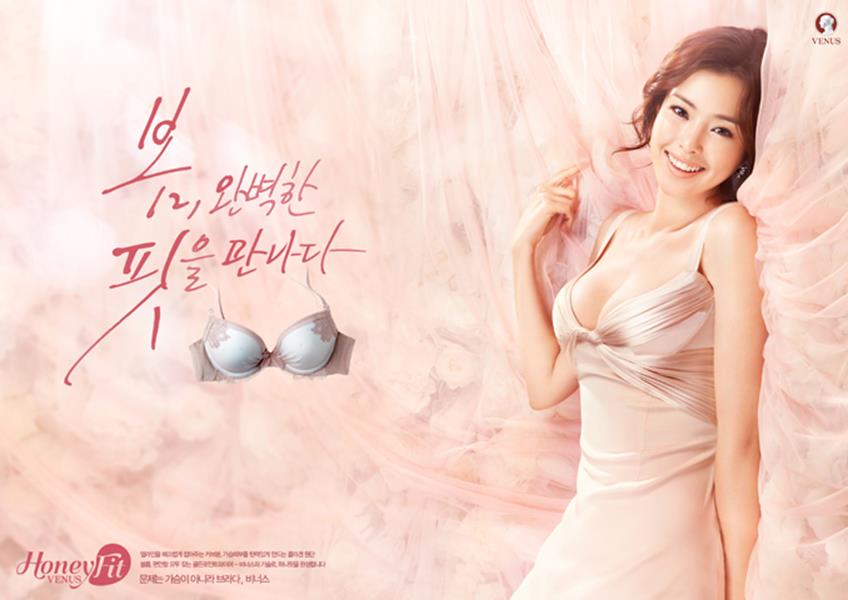
비너스 잡지 광고에 들어간 캘리그라피. 나무젓가락과 A4용지를 이용해 작업했다
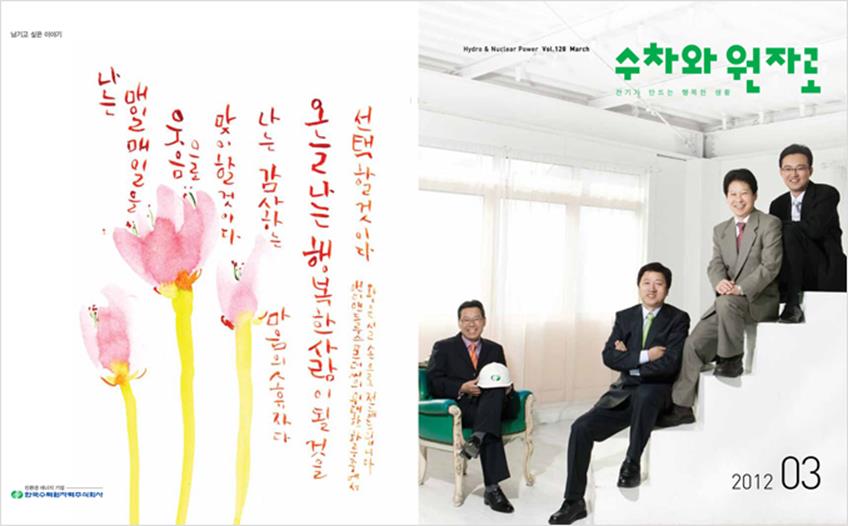
한국수력원자력주식회사 사보 <수차와 원자로> 3월호. 그림은 동양화물감으로 판화지에 그렸고, 글씨는 세필을 사용해 동양화물감으로 썼다
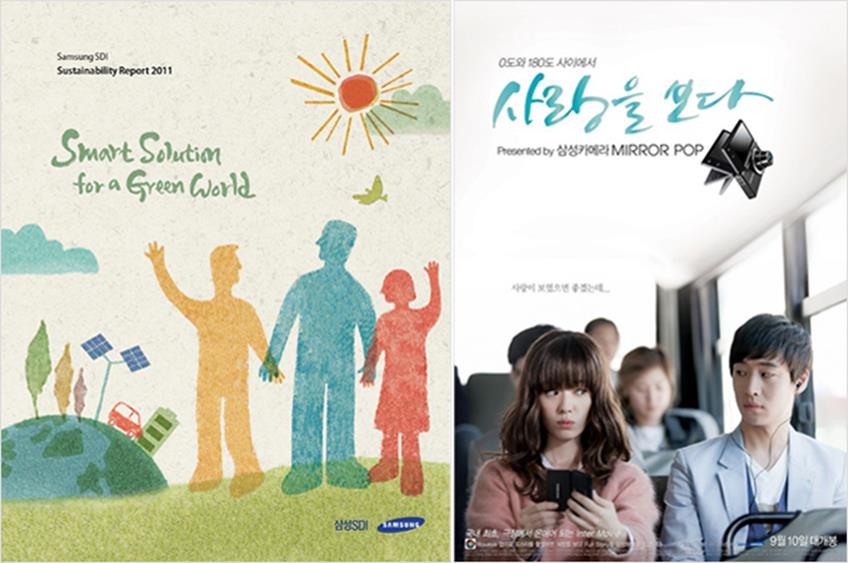
(왼쪽) 삼성카메라 미러팝 광고 작업. 수채화 물감으로 스케치북에 세필을 이용하여 작업했다. (오른쪽) 삼성SDI 사보표지. 갖고 있던 드로잉북에 물감을 사용해 작업한 사례.
최종적으로 선택된 글씨와 그림만 본다면 결과물은 하나입니다. 하지만 시안을 만들 때 여러 시도를 하게 되는데요. 붓은 기본이고, 세필, 붓펜, 나무젓가락 등을 이용해 컨셉트에 맞게 보통 다섯 개 내외의 시안을 만들어 클라이언트에게 선택권을 줍니다.
서예와 캘리그라피
캘리그라피 정의 다음에 가장 많이 받는 질문 중 하나는 ‘캘리그라피와 서예의 차이’에 대한 것입니다. 시각디자인에 사용되는 캘리그라피와 서예의 다른 점은 무엇일까요? 우선 서예는 서법을 통해 임서(臨書, 따라 쓰기)를 기본으로 오랫동안 공부하고 연구하여 작가로써 자신의 생각을 전시나 퍼포먼스 등으로 표현하는 과정을 거칩니다. 저도 서예를 공부하던 시절 많은 문헌을 참고했습니다. 모든 이들이 필자가 참고한 자료를 이용해 동일한 방식으로 공부하고 연습하는 것은 아닙니다. 더 많은 자료를 이용한 더 다양한 방식이 있다는 사실을 염두에 두길 바랍니다.
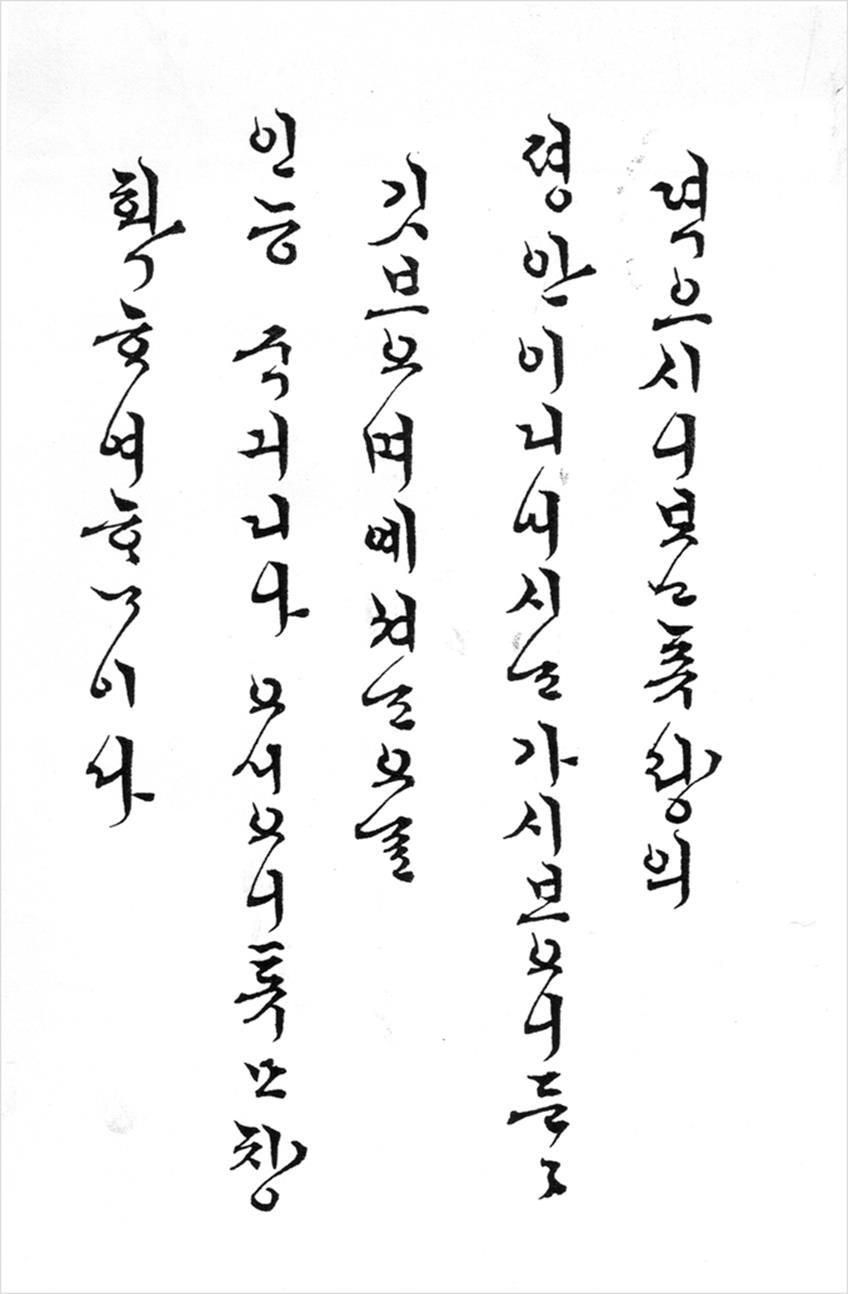
<봉셔>
한글서예는 크게 판본체(版本體), 궁체(宮體), 민체(民體) 등으로 나뉘고, 그 속에서 필사본, 궁체정자, 흘림, 진흘림 등과 같이 세분화되고 있습니다. 먼저 <봉셔>(봉서)는 왕과 왕후가 친척이나 암행어사와 같이 아래 사람에게 내리던 서간문으로 알려져 있습니다. <봉셔>는 개인적으로 좋아했던 자료인데요. 보다시피 글씨와 글씨 사이에 흘려지는 선들이 아름다우면서 견고합니다. 제가 흘려 쓴 글씨를 자주 쓰게 된 계기도 어찌 보면 <봉셔>의 영향일지 모르겠습니다. 대학시절에 한글을 접하고 <봉셔>를 보자마자 푹 빠져버려 열심히 따라 쓰기를 했던 기억이 납니다.
한문서예는 해서(楷書), 행서(行書), 초서(草書), 전서(篆書) 등 크게 네 가지로 나뉩니다. 각 분야별로 많은 작가들이 있고 비석을 탁본한 법첩들이 무수히 많지만, 그 중에서도 잘 알려진 작가와 작품으로는 왕희지의 <난정서>를 들 수 있습니다. <난정서>는 행서첩(行書帖)입니다. 우리가 사용하고 있는 활자체에 비교해 간단하게 설명하면, ‘해서’는 글자를 또박또박 쓴 서체를 말하고, 행서는 그것을 약간 흘려서 쓴 서체라고 보면 됩니다. 알려진 바에 의하면 <난정서>는 왕희지가 유흥에 젖어 있을 때 썼다고 합니다. 개인적으로 긴장해서 쓴 글씨보다 자연스러운 필체를 좋아해 왕희지의 <난정서>에 빠져 들었습니다.
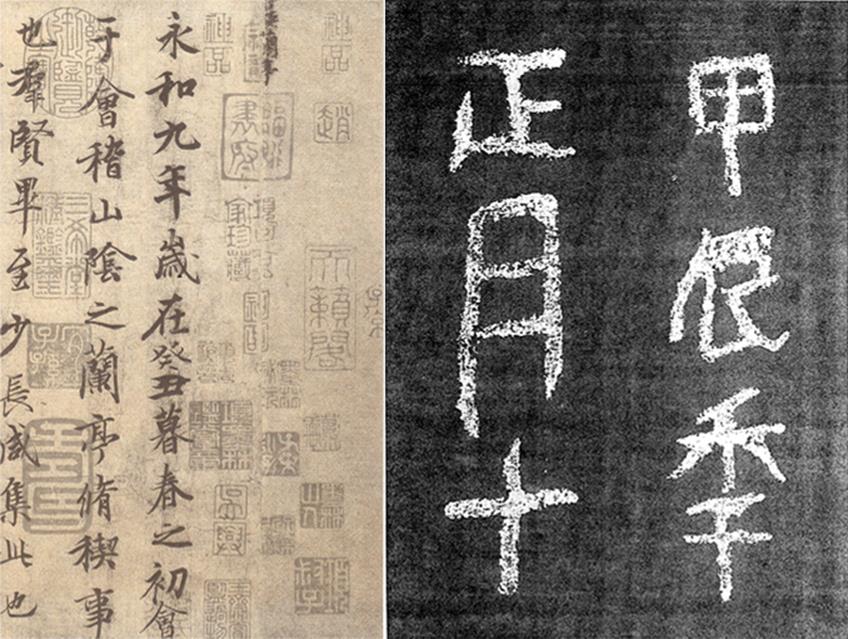
왕희지의 <난정서>(蘭亭序)와 <봉평비>(鳳坪碑)
<봉평비>의 정식 명칭은 <울진봉평신라비(蔚珍鳳坪新羅碑)>입니다. 국보 제242호로 우리나라의 몇 개 되지 않는 보존 비석 중 하나죠. 이 글씨를 보면 알겠지만 한 글자 한 글자 정형적인 모습에서 많이 벗어나 있습니다. <봉평비>는 부정형적이면서 순박한 글자 형태가 좋아 공부했던 비첩입니다. 이 외에도 좋아하는 우리나라 비석 중에 <광고태호태왕비>가 있는데, <봉평비>보다 정형적이면서 순박한 획의 질감을 보여줍니다.
저는 기본적으로 위와 같은 법첩들을 보고 서예를 공부했습니다. 이 외에도 더 많은 비첩들을 참고해 보고, 듣고, 쓰며 연습했죠. 임서, 즉 따라쓰기를 통한 공부 속에서 ‘나’만의 개성과 특징을 찾아 글씨를 다양하게 쓰고 싶다는 의지를 다질 수 있었습니다. 캘리그라피에 빠르게 적응하고 발돋움 할 수 있었던 데에도 서예라는 기본 바탕이 있어 가능하지 않았나 짐작해 봅니다.
컨셉트와 도구
자, 이제 실무에 적용되는 이야기를 해볼까요. 캘리그라피는 나 자신의 느낌 보다는 의도한 이의 생각에 맞게 컨셉트를 표현하는 것이 우선시 됩니다. 글자를 보는 이가 모두 다르기 때문에 기준이 애매할 수도 있지만, 최대한 클라이언트의 의도에 맞추며 작가로서 표현한 글자디자인에 대한 의도와 표현을 서로 소통하면서 만들어가는 과정이 캘리그라피입니다. 예를 들어볼까요. ‘바람이 분다’는 글자를 써달라는 의뢰를 받았다는 가정 하에 여러 도구를 활용해 시안을 만들어 보았습니다.
우선, 글씨를 쓰기 위해서는 사용 범위를 정확하게 알아야 합니다. 포스터, 광고, 신문, 상품, 책 표지 디자인 등 글씨가 어디에 사용되는지 먼저 파악해야 하죠. 글씨는 전체 레이아웃 사이즈에 따른 구성과 이미지, 폰트의 배치에 따라 다르게 써야 하기 때문입니다. 이런 다양한 조건들이 타이틀에 미치는 영향이 매우 큽니다. 글줄에 따른 표현과 강조되는 글자에 따라 표현되는 글씨의 이미지도 달라지죠. 그 중에 가장 중요한 것이 바로 ‘컨셉트’라고 생각합니다. 가벼움, 무거움, 부드러움, 세련됨, 슬픔, 기쁨 등 어떤 컨셉트냐에 따라 글씨를 쓰는 도구와 방식이 달라지기 때문입니다.
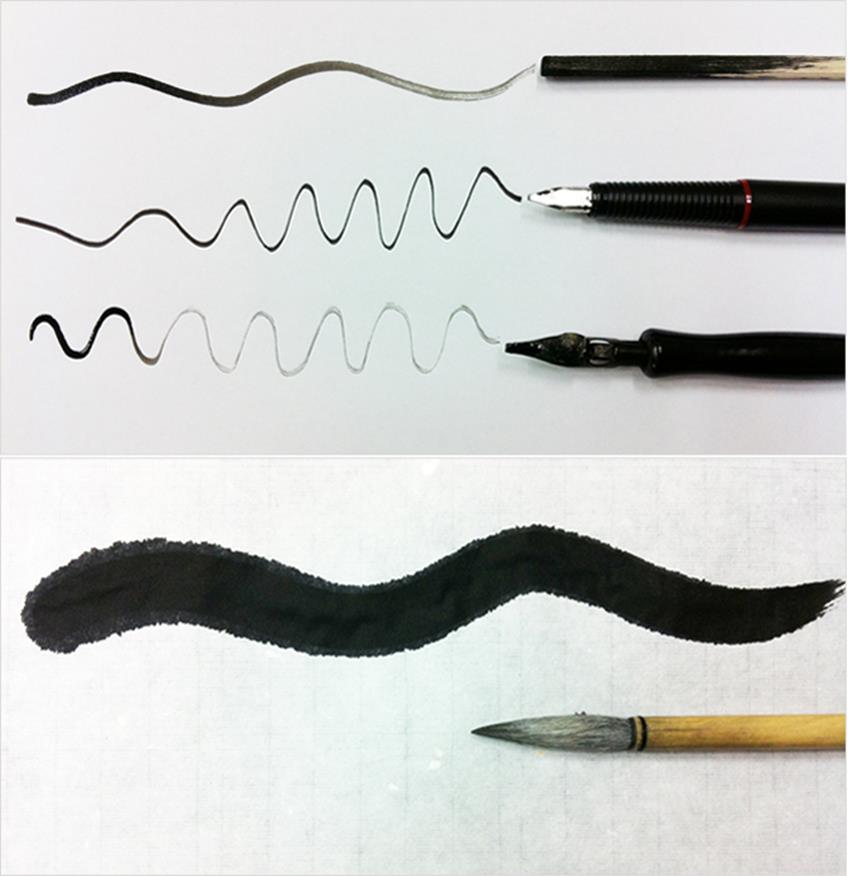
나무젓가락, 만년필, 펜촉, 붓으로 표현된 각기 다른 느낌의 선
위에 예로 보여준 것보다 더 다양한 도구가 있지만 자주 사용하는 도구 중에 나무젓가락이 있습니다. 위 예에서는 일반적인 모양의 젓가락을 사용했지만 젓가락을 깎아서 쓰거나 부러뜨리기도 합니다. 털이 없는 젓가락은 자주 찍어 쓰고 특히 화선지에 쓸 때 처음에 많이 번지는 특징이 있어 먹물 조절을 잘 해야 합니다.
그리고 만년필은 잉크를 담아 사용하는 반면, 펜촉은 잉크나 먹물을 찍어 쓰기 때문에 다른 효과를 낼 수 있습니다. 이 도구들은 화선지 위에서는 많이 번져 의도치 않게 큰 점들이 많이 찍히기 때문에 A4 용지와 같은 종이에 사용하면 깔끔한 작업이 가능합니다. 화선지에는 많이 번질 수 있어 강약 표현에 효과적죠.
붓은 다양한 서체를 표현하기에 좋은 ‘털’을 갖고 있어 화선지와 가장 잘 맞습니다. 귀엽게, 부드럽게, 때로는 거칠게 발묵 효과를 활용해 다양한 먹색을 표현할 수 있습니다. 이처럼 다양한 도구들의 특징을 살펴 글씨를 쓰게 됩니다.
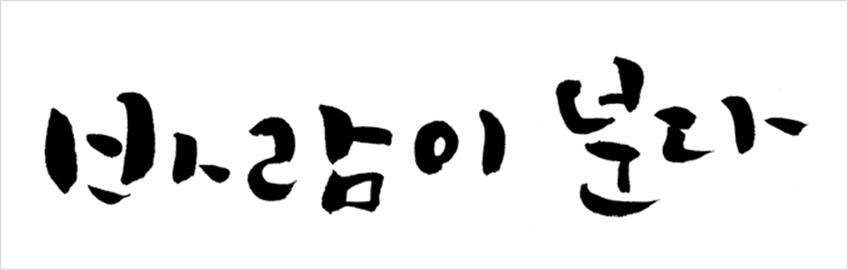
획을 짧게 표현하여 귀여운 느낌으로 쓴 글씨다. 개인적인 경험상 패키지디자인에 많이 썼던 글씨 형태이다
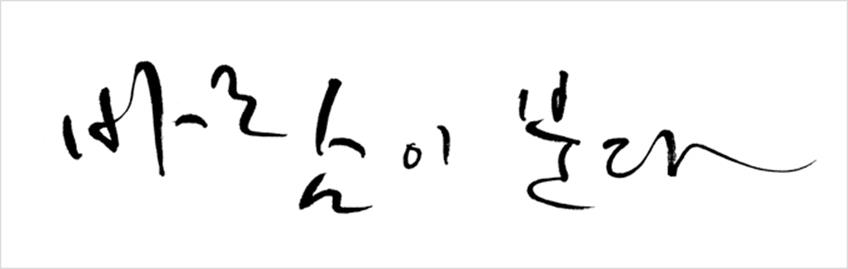
바람에 꽃잎이 흩날리듯 글씨도 흩날리듯 썼다. 이런 글씨 형태는 상품디자인처럼 가독성이 명확해야 하는 프로젝트 보다 영화, 콘서트, 뮤지컬 등에 사용하면 적당한 글씨 형태다. 광고카피에도 쓰일 법하지만 가독성 문제로 개인적인 포스터에 더 많이 사용했다
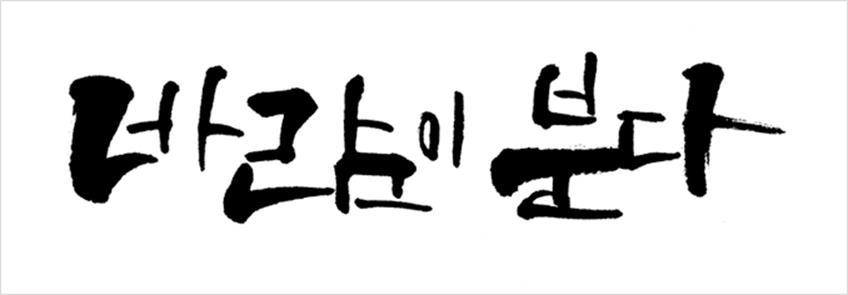
한 글자를 구성하고 있는 획 굵기의 대비를 크게 보여준 글씨다. 획 굵기를 달리해서 딱딱한 느낌이 덜하다
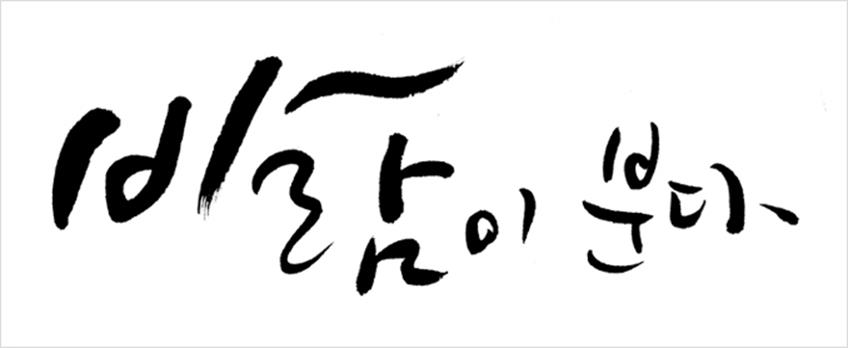
‘바’라는 글자의 ‘ㅏ’ 부분에 ‘-‘를 길게 늘어뜨려 바람이 부는 느낌을 표현했다. “바람”이라는 글자만 강조하고 나머지 글자들은 위 예시보다 조금 더 읽기 편하게 표현해 보았다
세로형태 예시. 가운데 중심이 아닌 오른쪽 중심으로 글씨를 썼다. 보는 이에 따라 조금씩 달라 보이겠지만 갈대가 연상되도록 작업했다. 오른쪽은 세로와 가로를 섞어서 쓴 구성이다. ‘바람’은 세로구성으로 쓰고 ‘분다’는 가로 형태로 표현해 보았다
위에서 보여준 사례는 디자인 범위에 따라 글씨를 얼마나 다양하게 표현할 수 있는지 보여줍니다. 이렇게 한 문장, 하나의 단어를 쓰더라도 컨셉트에 따라 도구에서부터 구성까지 온전히 파악하고 있어야 합니다. 써 놓은 글자를 세로 형태를 가로로 조합한다든지 여기저기에서 한 글자씩 조합해 짜깁기하지 않길 바랍니다. 이렇게 첫 번째 이야기를 마치도록 하겠습니다. 다음에는 우리 주변에서 흔하게 듣고, 보는 것들을 캘리그라피로 표현해 직접 쓰고 컴퓨터에 옮기는 방법 등에 대해 알아보겠습니다.